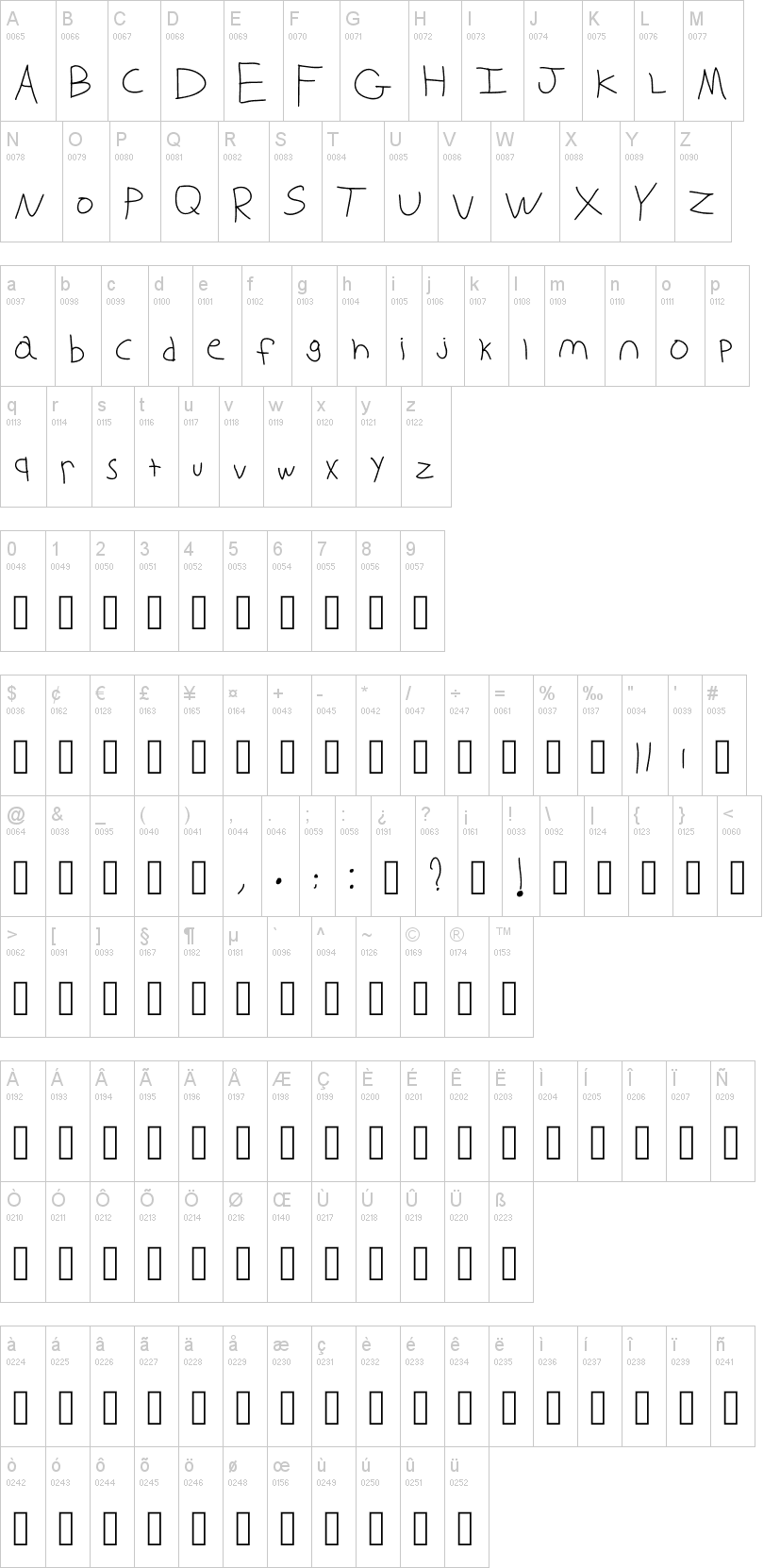
Kids
Kids 字体是一款专为少儿设计的字体,它具有清晰、简洁和可爱的特点。它的字体结构简单,易于识别,尤其适合少儿阅读和书写。Kids 字体的字体风格温和,可以让孩子们更容易理解和接受,而且还可以提高他们的学习动力。此外,Kids 字体还具有良好的可读性,更容易被孩子们理解,从而提高他们的阅读体验。
Kids是一款非常不错的手写艺术字体,具有很好的视觉感,适合于文化类的宣传设计、商业类品牌的广告和产品包装设计以及个性化文字排版等较多场景。